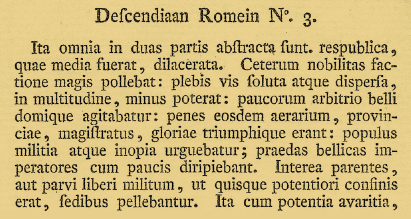
Erhard Kaiser (Quedlinburg, 1957) studeerde letterontwerpen en typografie aan de Hochschule für Grafik und Buchkunst te Leipzig. Daar leerde hij letters tekenen in de door de beroemde Duitse letterontwerper, typograaf, kalligraaf, auteur en leraar Albert Kapr (1918–1995) opgezette traditie. Van 1983 tot 1991 werkte hij aan lettertypen voor fotozetsel voor Typoart, destijds de grootste fontproducent in het voormalig Oostblok, waar Kapr de art director was. Van 1986 to 1992 doceerde Kaiser zelf het vak ‘Letterontwerpen en typografie’ aan de hogeschool van Leipzig.
In 1992 kreeg Erhard Kaiser van de Dutch Type Library de opdracht voor het maken van een digitale revival, gebaseerd op werk van de Duitse stempelsnijder Johann Michael Fleischmann (1707–1768). Op basis van verschillende door Fleischmann gesneden lettertypen maakte Kaiser voor dtl Fleischmann aparte versies voor de grote en de kleine corpsen, die vervolgens door hemzelf, dtl en urw++ te Hamburg handmatig in het ikarus formaat werden gedigitaliseerd. De tekensets werden verder uitgebreid door de dtl Studio. De uiteindelijke PostScript Type1, TrueType en OpenType fonts voor macOS en Windows werden door de Dutch Type Library geproduceerd.
dtl Fleischmann is bijzonder compleet: er zijn aparte optekeningen voor de grote en kleine corpsen, kleinkapitalen, uitgebreide reeksen ligaturen, speciale cijferreeksen, etc. In Duitsland wordt gesproken van ‘Kaisers Königliche Fleischmann’. Kaisers vakmanschap komt duidelijk tot uiting in deze uitermate geslaagde revival.
Naast dtl Fleischmann ontwierp Kaiser tevens de lettertypen dtl Antares en dtl Prokyon voor de Dutch Type Library.
Erhard Kaiser
Voor de displayversie (boven) werden andere originelen van Fleischmann gebruikt dan voor de tekstvariant (onder)